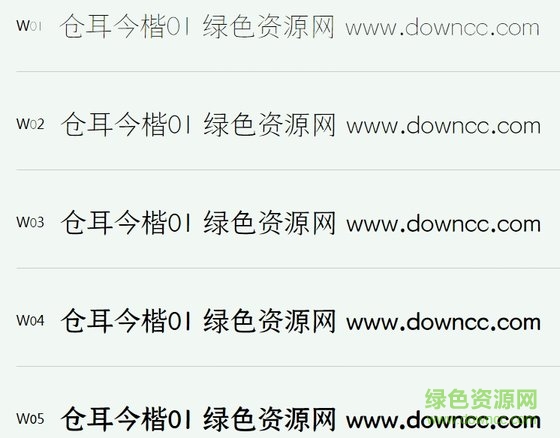
倉(cāng)耳今楷字體是倉(cāng)耳字庫(kù)的第一套字體,全名倉(cāng)耳今楷01,包括W01、W02、W03、W04、W05五個(gè)字重,給人不同的深淺大小選擇,給讀者更加直觀的閱讀體驗(yàn),讓文字顯得更加沉穩(wěn)大氣,綠色資源網(wǎng)誠(chéng)意推薦!
倉(cāng)耳今楷01有W01、W02、W03、W04、W05五個(gè)字重,可以滿(mǎn)足不同的應(yīng)用場(chǎng)景和媒介。號(hào)稱(chēng)“中國(guó)第一套楷體家族字庫(kù)”。說(shuō)來(lái)也是,目前面世的楷體都只有一種字重。倉(cāng)耳今楷01,從筆形、布白、結(jié)體、排版四個(gè)方面進(jìn)行了深入研究,呈現(xiàn)出舒適的閱讀效果。